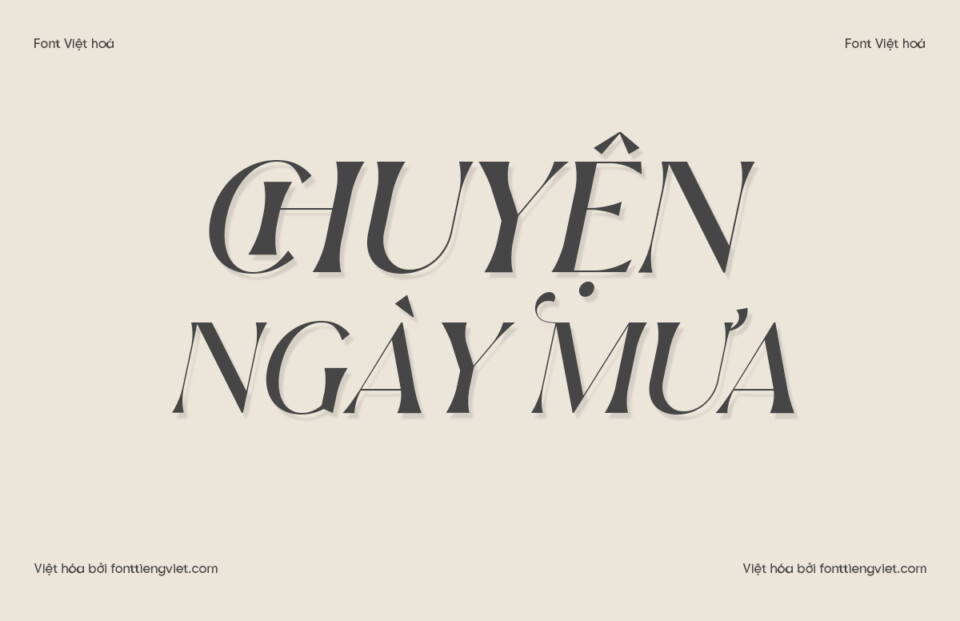
Font Việt hóa 1FTV VIP Brown Volky Italic
Trong thế giới đồ họa hiện đại, việc tìm kiếm một bộ Font Miễn Phí chất lượng và hỗ trợ đầy đủ tiếng Việt luôn là ưu tiên hàng đầu của các nhà thiết kế. Font Việt hóa 1FTV VIP Brown Volky Italic nổi lên như một hiện tượng nhờ sự kết hợp hoàn hảo giữa nét chữ thanh thoát và phong cách nghiêng đầy cá tính. Đây là lựa chọn lý tưởng cho những ai muốn thổi hồn vào các tác phẩm nghệ thuật, từ logo thương hiệu đến các ấn phẩm truyền thông học đường. Bộ phông chữ này không chỉ đơn thuần là công cụ soạn thảo mà còn là biểu tượng của sự sáng tạo không giới hạn, giúp truyền tải thông điệp một cách mạnh mẽ và tinh tế nhất đến người xem.
Khám phá sức hút của Font Việt hóa 1FTV VIP Brown Volky Italic
Điều làm nên sự khác biệt của Font Việt hóa 1FTV VIP Brown Volky Italic chính là cấu trúc đường nét được chăm chút tỉ mỉ. Kiểu dáng Italic (nghiêng) mang lại cảm giác chuyển động, linh hoạt và rất hiện đại. Đối với các bạn học sinh và giáo viên, việc sử dụng bộ phông này trong các bài thuyết trình hay thiết kế báo tường sẽ giúp nội dung trở nên sinh động, bắt mắt hơn hẳn các phông chữ mặc định khô khan. Sự chỉn chu trong khâu Việt hóa giúp các dấu câu tiếng Việt được đặt vị trí chính xác, không bị lỗi hiển thị hay mất nét, đảm bảo tính thẩm mỹ cao nhất cho mọi văn bản.
Ứng dụng thực tế trong học tập và công việc
Font Việt hóa 1FTV VIP Brown Volky Italic cực kỳ đa năng trong nhiều tình huống sử dụng khác nhau. Với độ dày nét vừa phải, nó rất dễ đọc ngay cả ở kích thước nhỏ. Bạn có thể sử dụng bộ font này để làm tiêu đề cho các slide bài giảng, thiết kế thiệp mời sự kiện trường học, hoặc tạo ra những trích dẫn truyền cảm hứng trên mạng xã hội. Màu sắc thẩm mỹ mà bộ chữ này mang lại thường gợi liên tưởng đến sự sang trọng nhưng vẫn giữ được nét gần gũi, phù hợp với xu hướng thiết kế tối giản đang thịnh hành tại Việt Nam hiện nay.
Ưu điểm vượt trội khi sử dụng Font Việt hóa 1FTV VIP Brown Volky Italic
Lưu ý khi phối hợp màu sắc và bố cục
Để phát huy tối đa vẻ đẹp của Font Việt hóa 1FTV VIP Brown Volky Italic, bạn nên kết hợp với những tông màu trầm ấm như nâu đất, vàng đồng hoặc xanh đen. Bố cục chữ nên được sắp xếp thoáng đãng để làm nổi bật những đường cong nghiêng đặc trưng. Đừng quên căn chỉnh khoảng cách giữa các chữ cái (kerning) một cách hợp lý để tạo ra sự cân đối về thị giác, giúp người đọc dễ dàng tiếp nhận thông tin mà không cảm thấy rối mắt.
Lời kết về bộ phông chữ độc đáo
Tóm lại, việc sở hữu Font Việt hóa 1FTV VIP Brown Volky Italic trong thư viện cá nhân là một bước đi thông minh cho bất kỳ ai yêu thích cái đẹp và sự chuyên nghiệp. Với sự hỗ trợ tận tình từ cộng đồng Font Miễn Phí, Font Việt Hóa, Font Việt hóa 1FTV VIP Brown Volky Italic, bạn hoàn toàn có thể tự tin tạo ra những sản phẩm thiết kế mang đậm dấu ấn cá nhân. Hãy tải về và trải nghiệm ngay hôm nay để thấy được sự thay đổi kỳ diệu trong các tác phẩm sáng tạo của mình, đồng thời nâng cao kỹ năng trình bày văn bản một cách bài bản nhất.